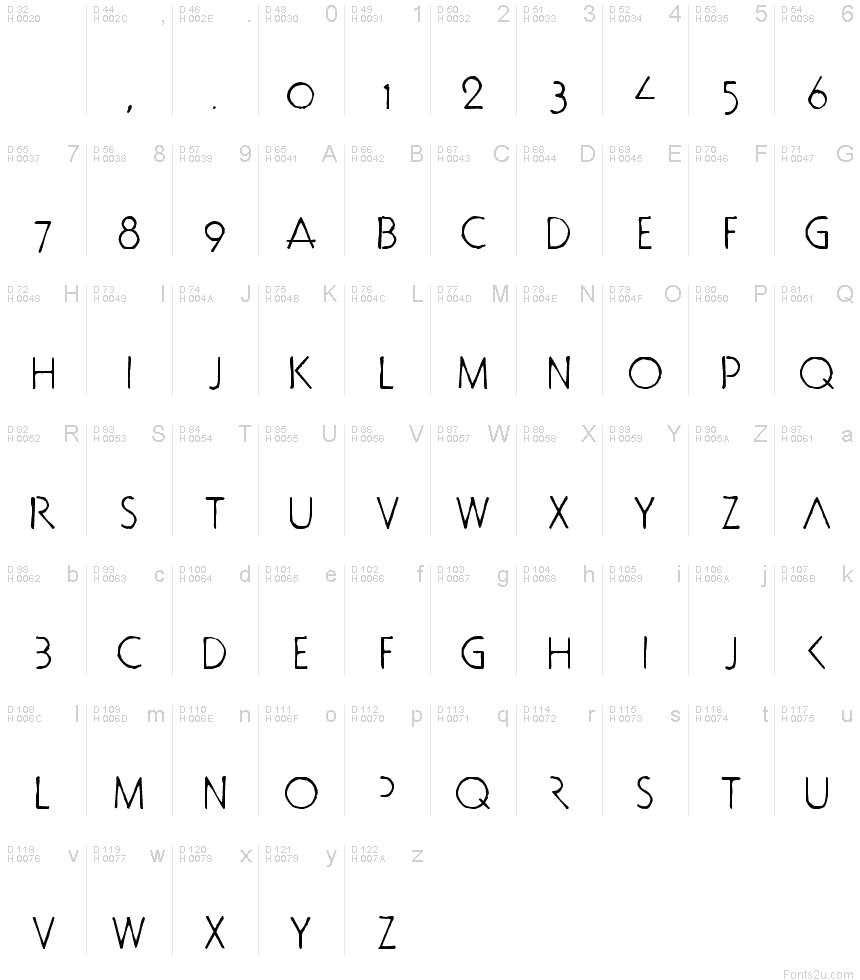
خط DoctorBob من تصميم joeBob graff-X هو خط عرض (display) مجاني متآكل يتمتع بطاقة غريبة ومضطربة. يبدو كل حرف وكأنه رُسم بقلم تحديد مهتز على زجاج مصنفر – أشكال دائرية متداخلة تبدو حوافها متآكلة قليلاً، كما لو أنها صُوِّرت ضوئياً أكثر من مرة. النتيجة تبدو مرحة ومقلقة في آنٍ واحد، وهي مزيج غريب من خطوط الـ DIY اليدوية ولوحات خيال علمي منخفضة الدقة (lo-fi).
باستخدام DoctorBob، تكتسب العناوين على الفور طابعاً خاماً و"أندرجراوند"، وهو مثالي لملصقات الحفلات الموسيقية، والمجلات المستقلة (zines)، والعلامات التجارية التجريبية، وعناوين أفلام الرعب والكوميديا، وأغلفة الألبومات المستقلة. كما تعمل الأشكال المفتوحة والهوائية بشكل جيد في قوائم الألعاب أو ملصقات العلوم الغريبة حيث تحتاج إلى خط مقروء وغير تقليدي. يتناسب هذا الخط المجاني جيداً مع خط sans هندسي نظيف ومصغر أسفله، مما يتيح لـ DoctorBob تولي مهمة العناوين الصاخبة والجذابة.